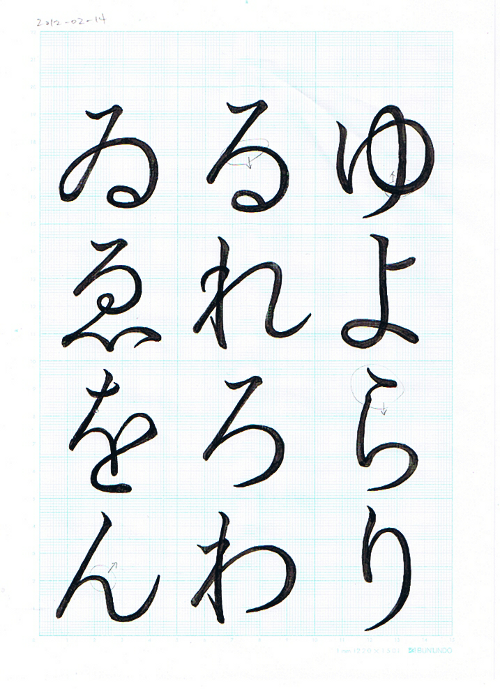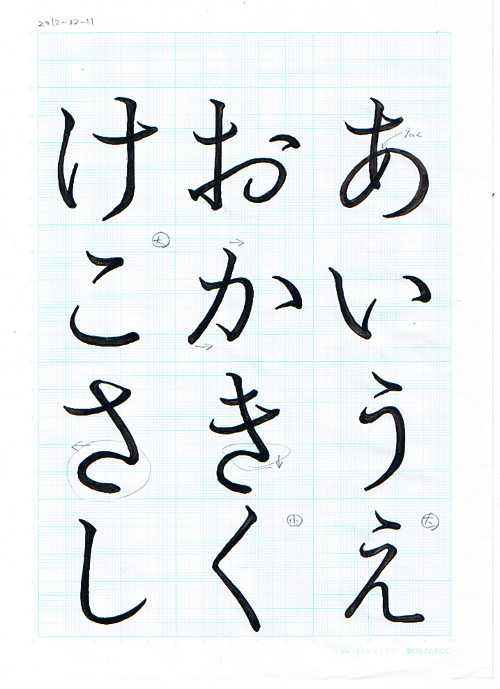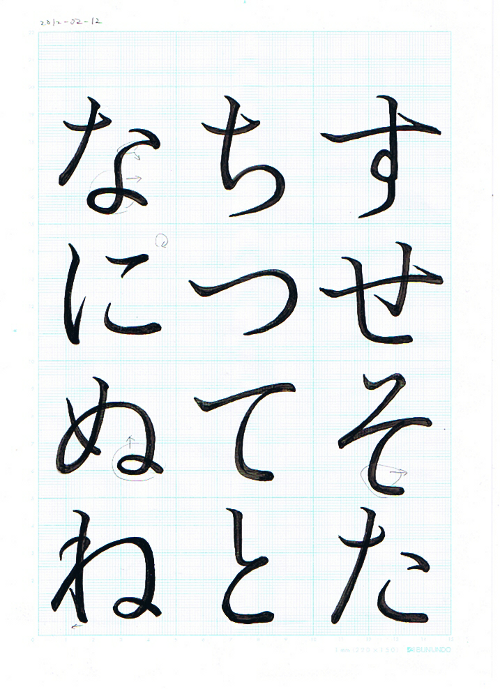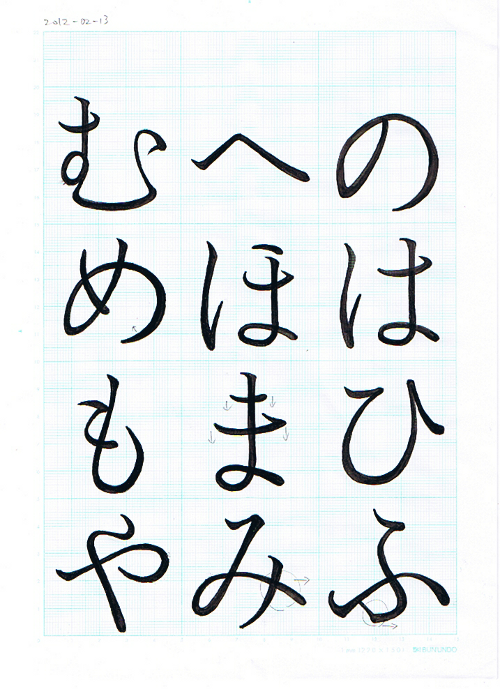
墨入れしてみた #かな書いてみる
前回で下書きが一通りできた(上の記事参照)。もう一回下書きを書き直して改良するか、それとも次の段階に進むか迷ったが、「とりあえずどんどん進んで困ったらそのとき考えよう」という楽天的な方針で行くことにした。というわけで、次の工程である清書(墨入れ)に進んでみる。
作業としては、下書きを透かして輪郭をトレースし、それを墨で塗っていくだけ。トレースには一番安かった*1下のトレース台を使ってみた。安いなりの造りだが、この用途で使うにあたっては今のところ特に不満もない。
輪郭を鉛筆で方眼紙にトレースしたら、それに墨入れをしていく。墨は墨汁をそのまま使った。筆は家にあった漢字書用の小筆を使ったが、本当は面相筆の方がいいのかもしれない。コシが強い筆の方が、線がフニャらずに良さげ。輪郭は筆の腹で描くとぶるぶるになるので、穂先側で描くようにする。また、自分の描きやすいように紙の向きを変えて描いていくと楽。といっても慣れないとやっぱりなかなか難しい。
一枚書き終わったら、出来を確認する。遠くから見てみたり角度を変えて眺めてみたり、いろいろと方法はあるだろうが、自分の場合、スキャンした画像を縮小表示で見てみると欠点がよくわかった。凹んでいる箇所やはみ出た箇所を墨と修正液で直したりして、何度かこの修整作業を繰り返す。
で、出来上がったのがこちら。
まだまだ統一感に欠けるところもあるが、とりあえずは一通り終わった。
さて次はどうしようか。